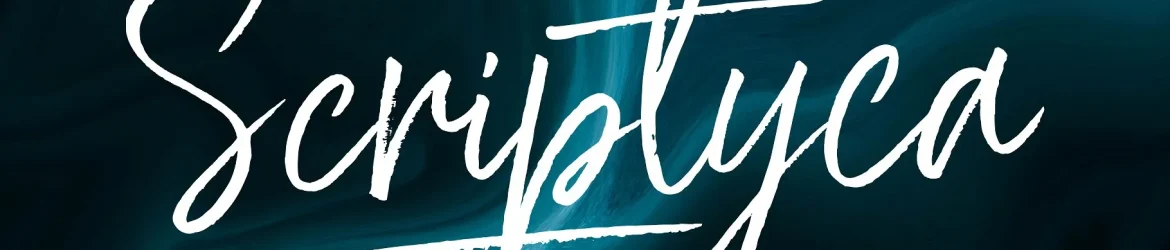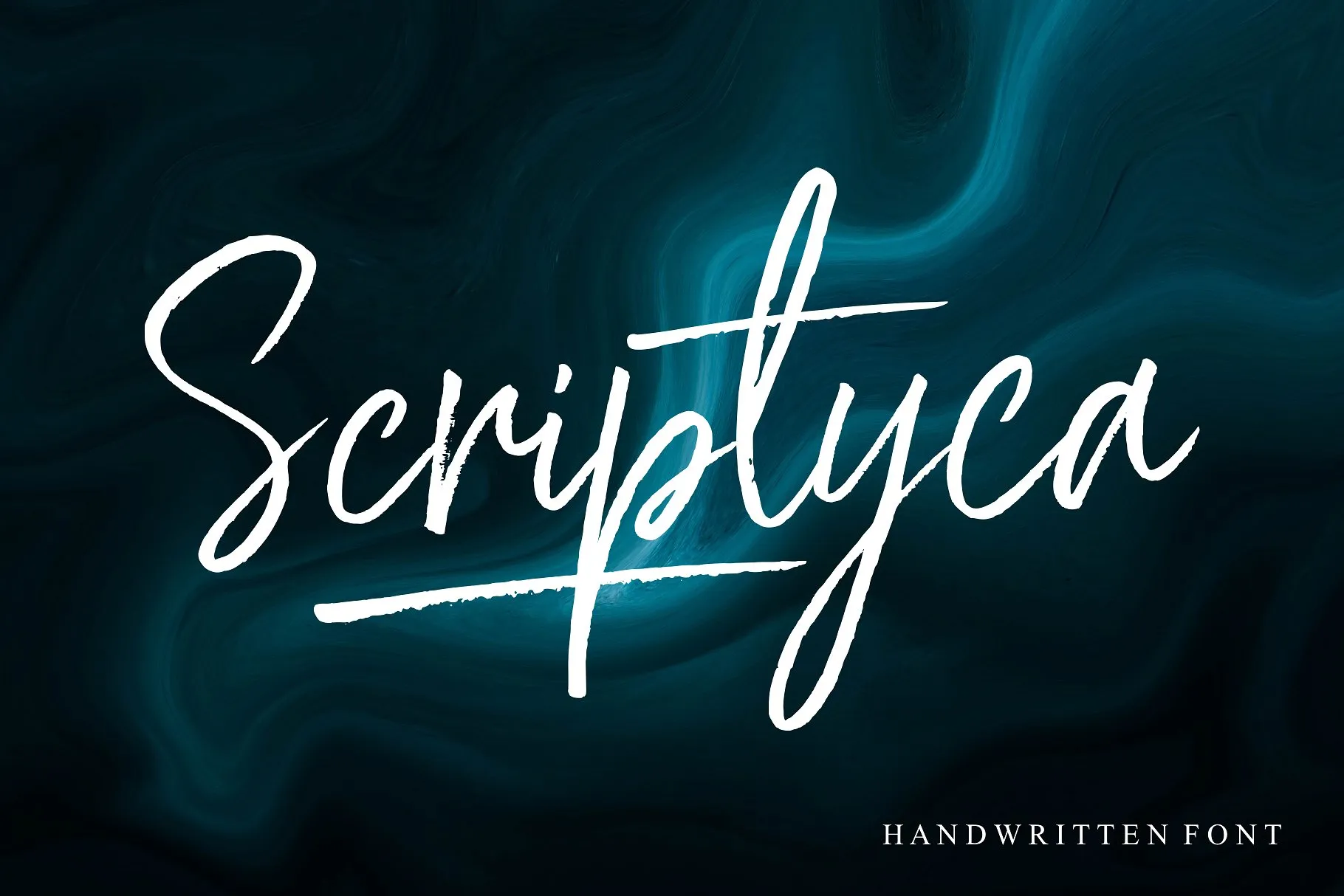
Scriptyca Brush Font
Bem-vindo a uma nova adição para seu arsenal de fontes de script! Introduzimos Scriptyca Font, que traz um toque moderno e elegante aos seus projetos. Este novo estilo brush adiciona um ar sofisticado e divertido à sua composição gráfica. Scriptyca é perfeito para incorporar em designs variados como textos de citações, convites de casamento, posters e até mesmo cartões personalizados que você pode presentear aos seus amigos e familiares. Esta fonte é ideal para uso em diversas áreas, desde a marca pessoal até o design de produtos e embalagens, ou simplesmente para um toque especial no seu trabalho social. Com Scriptyca, você terá uma fonte versátil que pode transformar seu projeto em algo único e divertido. Seja você designer de moda, blogueiro, influenciador digital ou criativo freelancer, esta é a fonte perfeita para complementar sua obra de arte visual. Descubra agora mesmo como Scriptyca pode revolucionar suas criações!